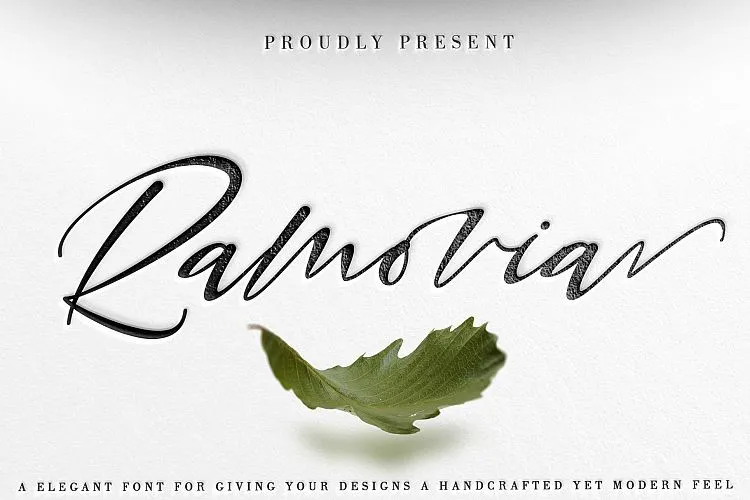
Ramovia Script Font
A Ramovia Script é uma fonte script moderna criada pelo designer f0rdesigner. Com seu estilo de caligrafia única e cuidadosamente produzida, ela oferece uma sensação elegante que dá um toque de handmade contemporâneo aos seus designs. Perfeita para criar padrões e backgrounds em sua criação ou cabeçalhos em menus, a Ramovia Script é linda em convites de eventos, cartas de boas-vindas, materiais de marca, cartão de negócios, citações, panfletos e muito mais. Com um aspecto limpo e bem feito à mão, ela brilha tanto no design moderno quanto no clássico, tornando-a uma opção ideal para designers buscando criar elementos únicos e atraentes em seus projetos visuais.